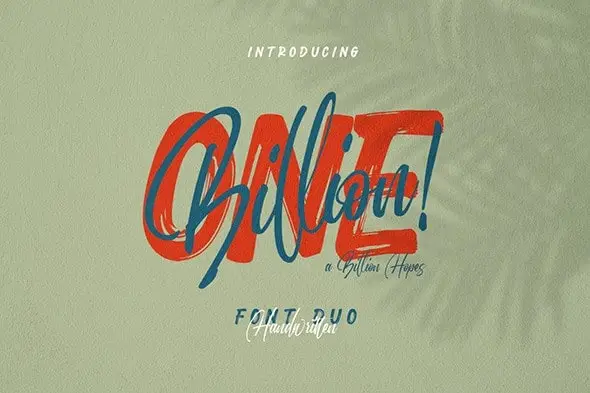
Onebillion Script Font Duo – Download Grátis
A fonte “Onebillion Script Font Duo” do designer Hamilton é uma família exclusiva que oferece duas estilos diferentes para uso profissional. Esse conjunto vem com uma grande variedade de caracteres bem organizados, incluindo espaçamento e kerning cuidadosamente feitos. Isso lhe dá inúmeras possibilidades quando está criando design tipográfico para seus projetos profissionais. Um dos estilos é perfeito para fazer um impacto, enquanto o outro combina-se de forma afeita para criar designs de tipografia belas – ideais para aplicativos de marca, folders, capas de livros, mídias sociais e até mesmo mercadoria. É uma fonte versátil que traz um toque especial ao seu design gráfico, seja você designer de logo ou editor de conteúdos online, essa família de fontes certamente lhe ajudará a destacar-se em seus projetos. Um bônus adicional é que esta fonte vem com uma demo gratuita para aqueles que desejam testá-la antes de investir no download do modelo final. Esta familia de fontes não apenas oferece design tipográfico, mas também leva muito cuidado nas pequenas detalhes, o que torna a criação de um texto impecável ainda mais simples e acessível para designers profissionais.